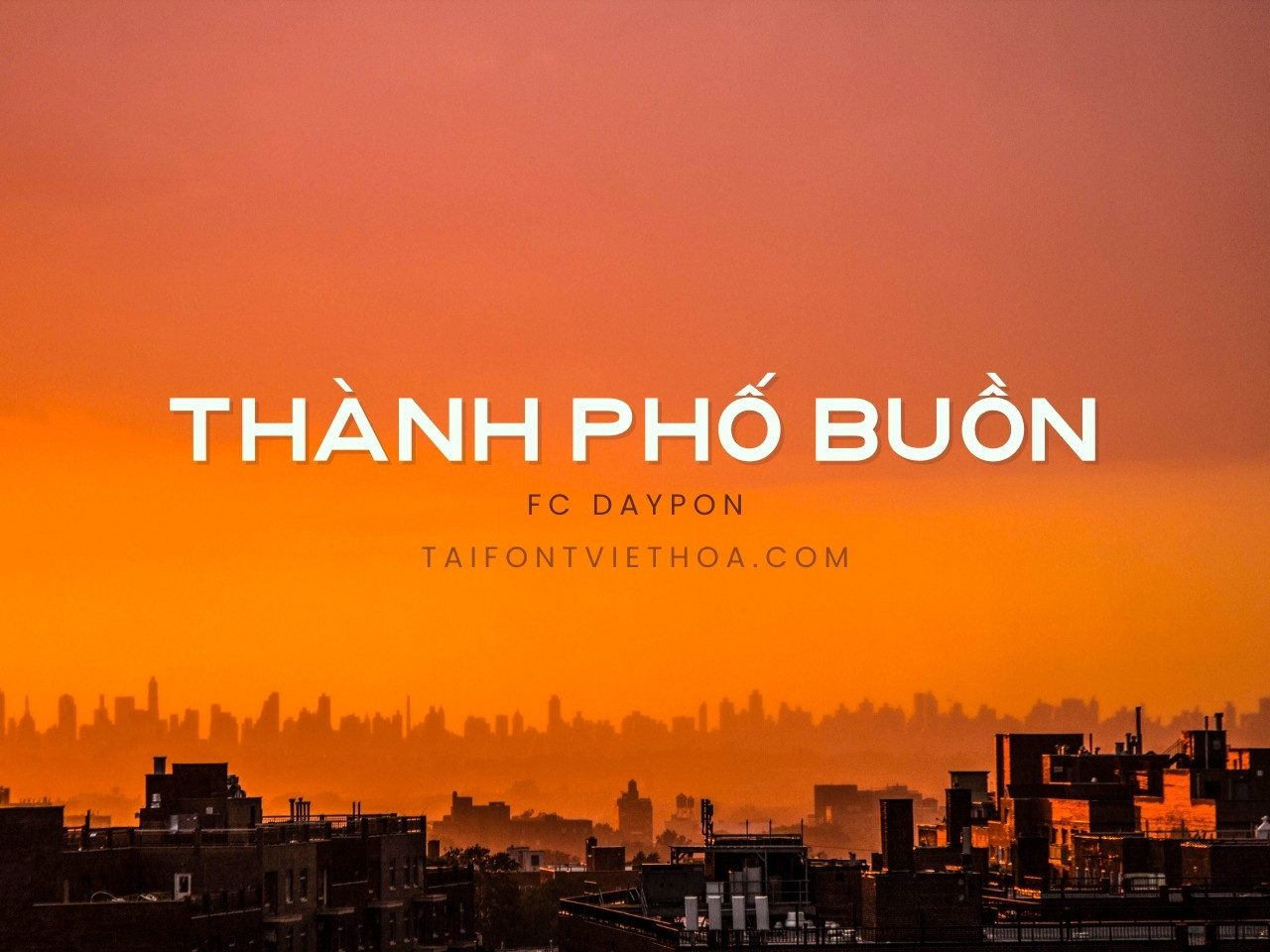
Font việt hóa FC Daypon
Giới thiệu về font Daypon và phiên bản Việt hóa
FC Daypon là phiên bản Việt hóa từ font gốc “Daypon” – một thiết kế font display độc đáo mang đậm phong cách retro hiện đại, được phát triển bởi Letterhend Studio (Indonesia). Font nổi bật nhờ các nét chữ dày, mạnh mẽ, kết hợp với hơi hướng hoài cổ của thập niên 70–80, thường thấy trong các biển hiệu cũ, poster ca nhạc cổ điển hoặc logo vintage. Với khả năng hỗ trợ hơn 60 ngôn ngữ sử dụng bảng Latin mở rộng, Daypon nhanh chóng được đón nhận rộng rãi trong cộng đồng thiết kế quốc tế.
Phiên bản Việt hóa FC Daypon do cộng đồng Font Chuẩn thực hiện, bổ sung đầy đủ dấu tiếng Việt và tối ưu hiển thị với chuẩn Unicode. Font được taifontviethoa.com tuyển chọn, sưu tầm và cung cấp nhằm phục vụ các nhà thiết kế cần một kiểu chữ vừa nổi bật vừa mang hơi hướng cổ điển – hiện đại, có thể áp dụng linh hoạt trong nhiều dự án thương hiệu sáng tạo.
Phong cách thiết kế retro – đậm chất trình bày và nhận diện
FC Daypon sở hữu các nét chữ to bản, đậm, vuông vức với phần bo góc nhẹ, tạo cảm giác vững chắc mà không khô cứng. Thiết kế chữ mang nhiều yếu tố hoài cổ nhưng vẫn giữ sự linh hoạt hiện đại, giúp tạo nên cảm giác thân thiện và chuyên nghiệp. Đặc biệt, bộ chữ cái in hoa được thiết kế cẩn thận với tỉ lệ hợp lý, hỗ trợ tốt cho việc tạo tiêu đề, slogan hoặc logo nổi bật.
Font này lý tưởng để sử dụng trong thiết kế logo, bảng hiệu, poster retro, bao bì sản phẩm sáng tạo hoặc ấn phẩm thương hiệu cá tính. Ngoài ra, FC Daypon còn rất phù hợp với các ngành nghề như quảng cáo, ẩm thực, tổ chức sự kiện, truyền thông sáng tạo, thời trang hoặc các sản phẩm giải trí đậm chất cá nhân hóa.